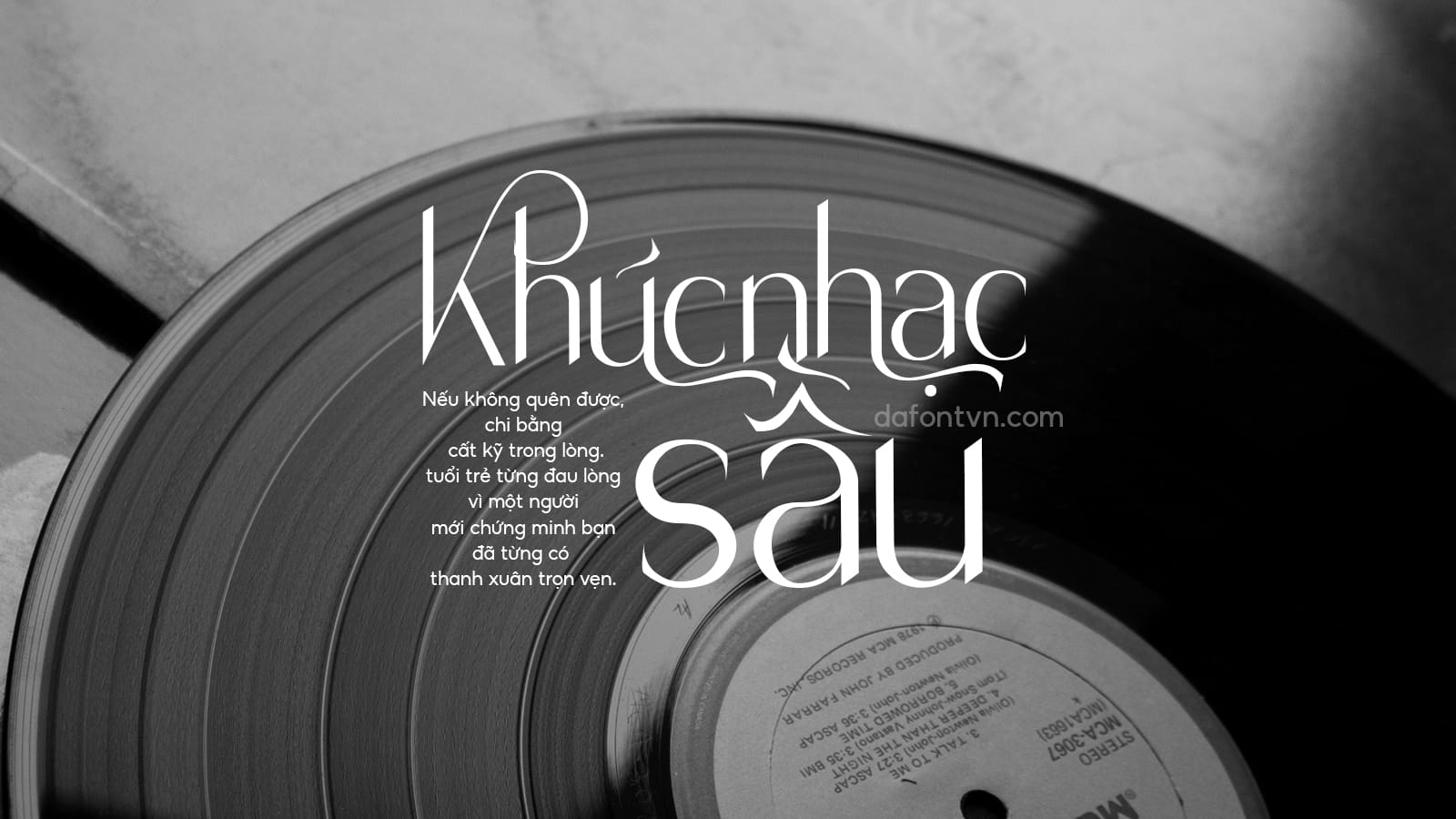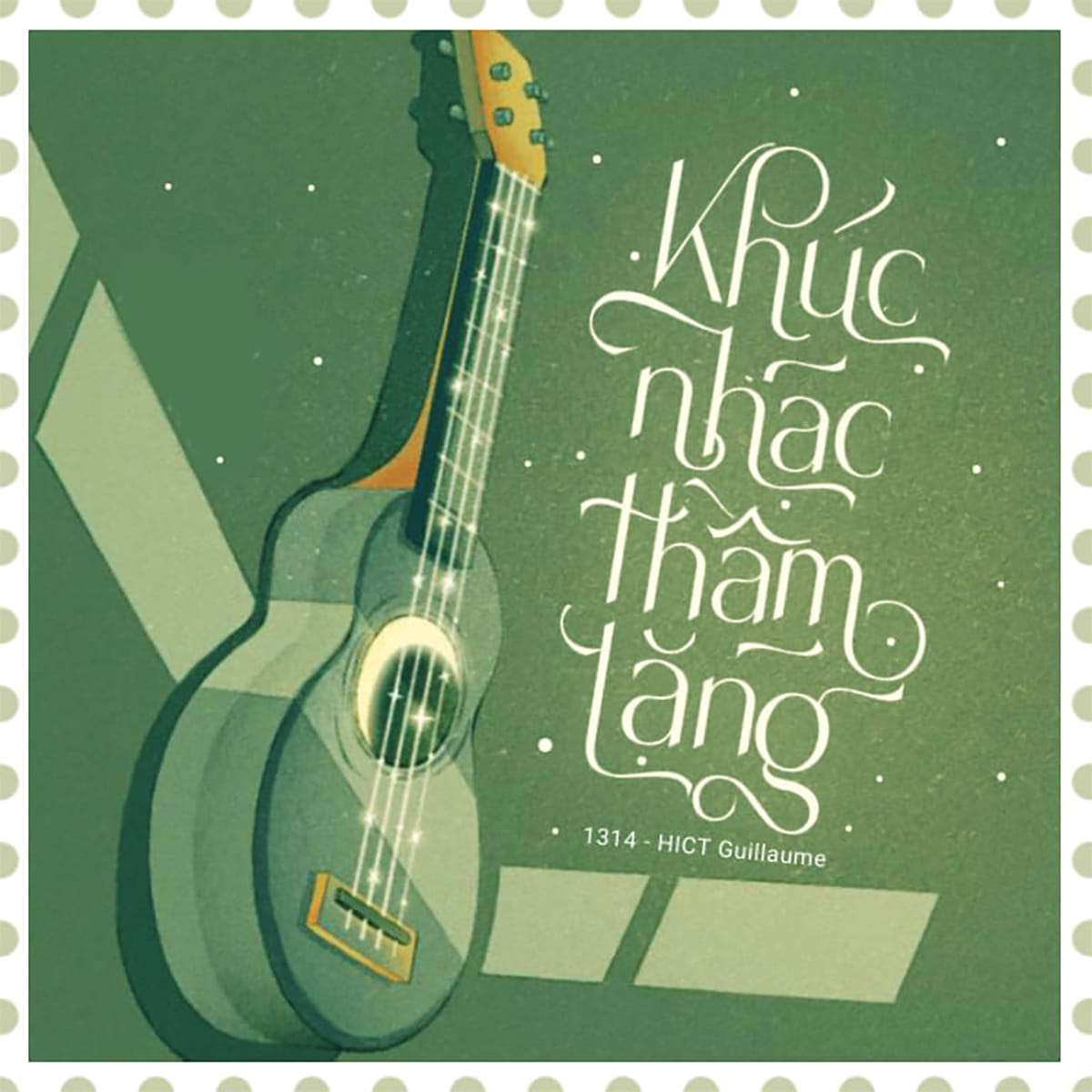
Font Abigan Việt Hóa – Font xịn xò
Font Abigan Việt Hóa là một font serif với các nét chữ được thiết kế sang trọng và các điểm nhấn sắc nét tạo thêm phong cách bóng bẩy và ấn tượng. Font chữ này hoàn hảo cho các dự án biên tạ, tiêu đề tạp chí, thiết kế logo, typographic, bao bì sản phẩm. Font được Việt Hóa bởi 1314 đi kèm với đầy đủ chữ hoa, chữ thường, mình đã chỉnh sửa và tối ưu lại font hoàn chỉnh và mã hóa PUA.
Font Abigan Việt Hóa preview 2